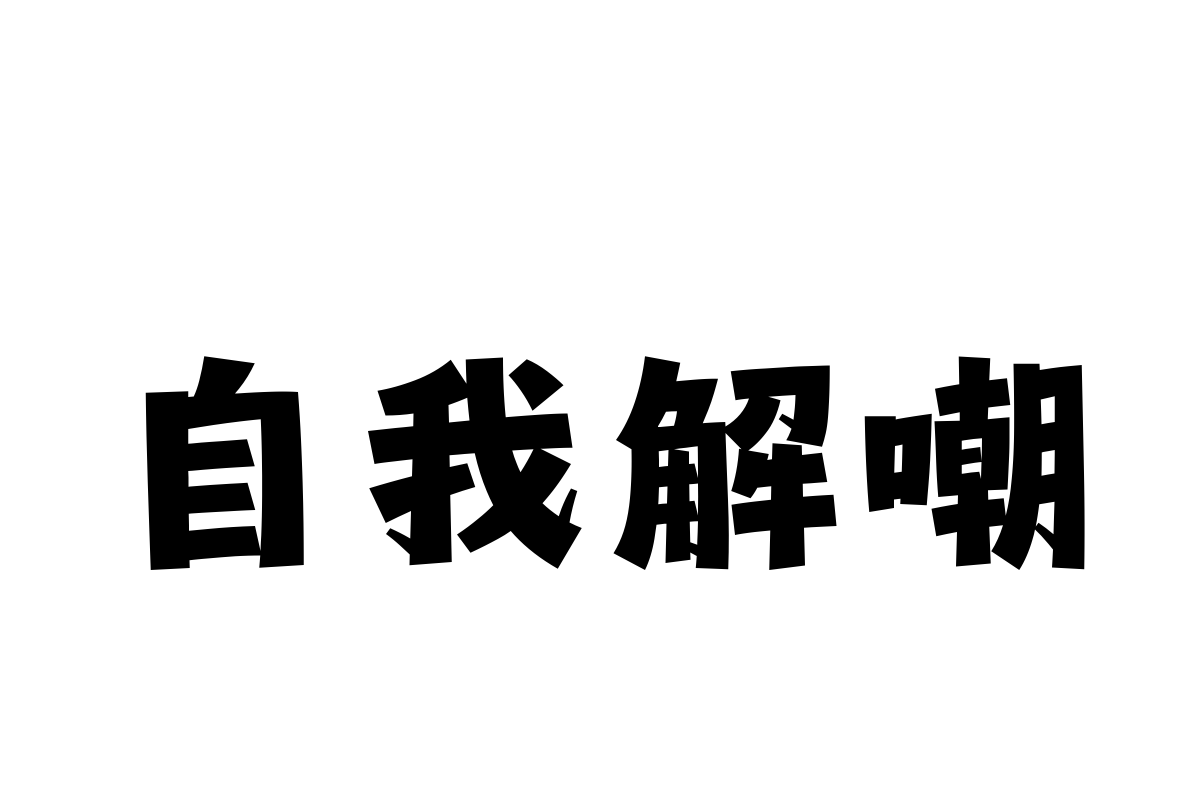
汉仪永字小侠客是一款由汉仪字库推出的中文字体,具有独特的艺术风格和强烈的视觉冲击力。这款字体采用了传统的书法笔触和现代的设计理念,将传统的汉字与现代的设计元素相结合,创造出了一种全新的视觉体验。
永字小侠客字体的特点在于其笔画流畅、结构紧凑,线条粗细变化丰富,既有古典的韵味,又不失现代感。它的字形结构独特,既有传统的韵味,又有现代的时尚感,适合用于各种需要强调个性和创意的设计场景。
此外,永字小侠客字体还具有很好的可读性,无论是在印刷还是在电子屏幕上都可以轻松阅读,不会因为字体大小的变化而影响文字的清晰度。这使得永字小侠客字体成为了设计师们非常喜欢的一款字体。